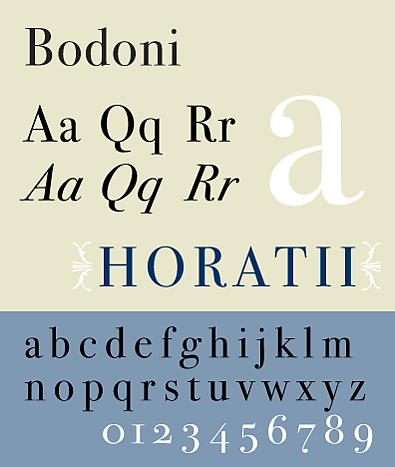
Бодони (шрифт)
Бодо́ни (англ. Bodoni) — семейство гарнитур, основанных на рисунке шрифта, разработанного в 1787 году итальянским шрифтовиком Джамбаттистой Бодони.
Общие сведения
| Бодони | |
|---|---|
| Стиль | Классицизм |
| Классификация | Антиква нового стиля (Didones) |
| Дата создания | 1787 |
| Дизайнер | Джамбаттиста Бодони |
| Использование | Рекламная и газетная продукция, журналы и альбомы по искусству[1] |
Описание
Шрифты Бодони характеризуются прежде всего очень большим контрастом — соединительные штрихи во много раз тоньше основных. Другая важная особенность шрифтов — засечки, которые отличаются не только малой толщиной, но и углом наклона по отношению к основным штрихам: в отличие серифов от ряда других шрифтов, у Bodoni они практически перпендикулярны. Штрихи шрифтов Бодони очень длинные и острые, а овалы — совершенно прямые[2]. Другие особенности:
- сильный наклон курсива (более 20°)
- латинская W имеет пересечение внутренних диагоналей (как в логотипе английской и других Википедии)[3]
На основе исходной гарнитуры Bodoni впоследствии были созданы новые шрифты данного семейства, в частности Bauer Bodoni.
Использование
Шрифты семейства Бодони больше подходят для набора заголовков, так как большие массивы текста, набранные Бодони, плохо читаемы[4].
Некоторые шрифты Бодони из-за очень тонких засечек плохо воспроизводятся офсетной печатью[5].
Титры фильмов Пазолини набраны именно данным шрифтом.
Версии гарнитур
Офисный пакет iWork (начиная с 8-й версии) компании Apple содержит следующие гарнитуры, представители семейства Бодони[6]:
- Bodoni Ornaments ITC TT — набор декоративных элементов, растительных виньеток и вензелей;
- Bodoni SvtyTwo ITC TT — гарнитура в формате TrueType;
- Bodoni SvtyTwo OS ITC TT — гарнитура с минускульными цифрами;
- Bodoni SvtyTwo SC ITC TT — гарнитура с капителью.
Компания Linotype предлагает 7 гарнитур ATF Bodoni, которые содержат 10 начертаний (курсив, полужирное, уплотненное и т. д.)[7]. Эти гарнитуры были разработаны американским дизайнером Моррисом Фуллером Бентоном (1872—1948) для фирмы ATF.
В 1989 году компания «ПараТайп» разработала гарнитуру, включающую кириллицу, позже в 1993 году было добавлено узкое начертание[2].